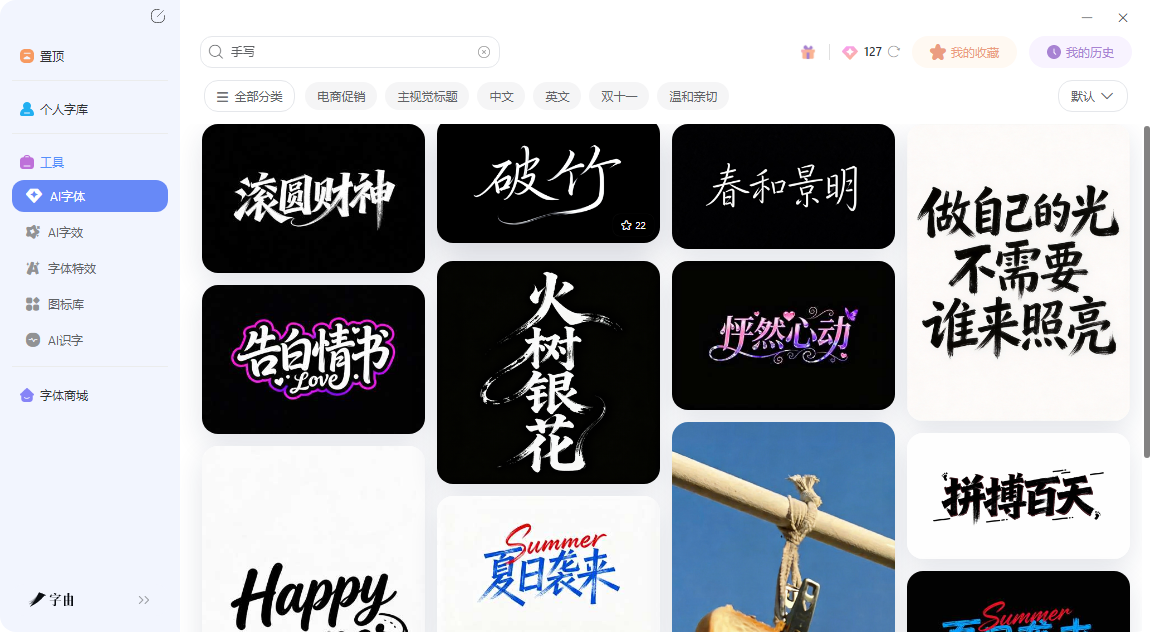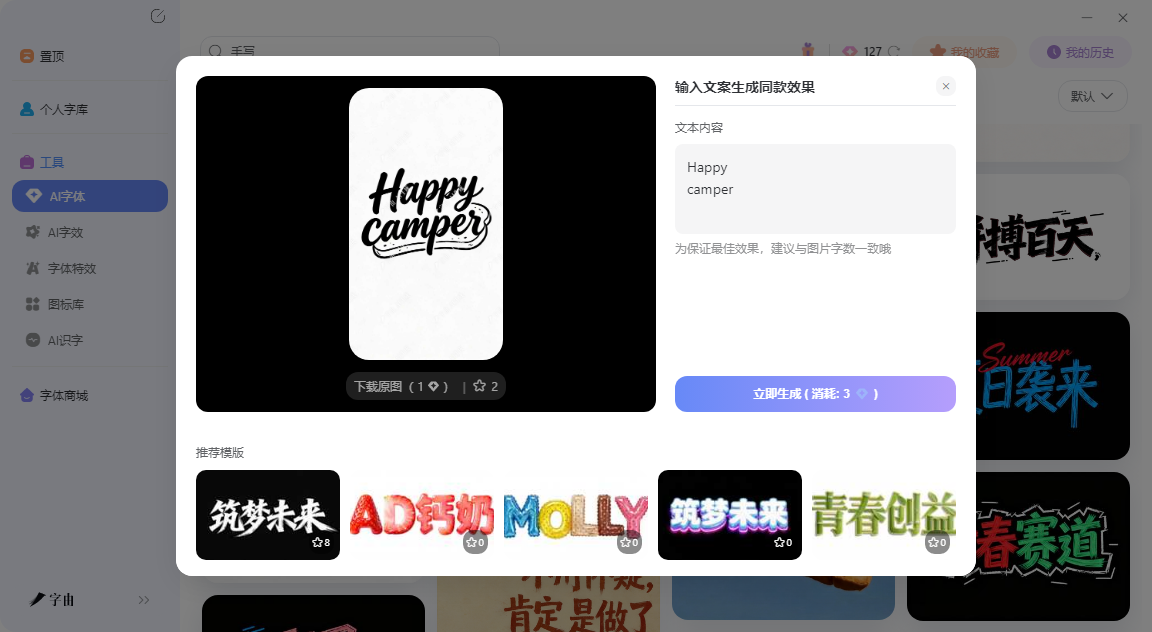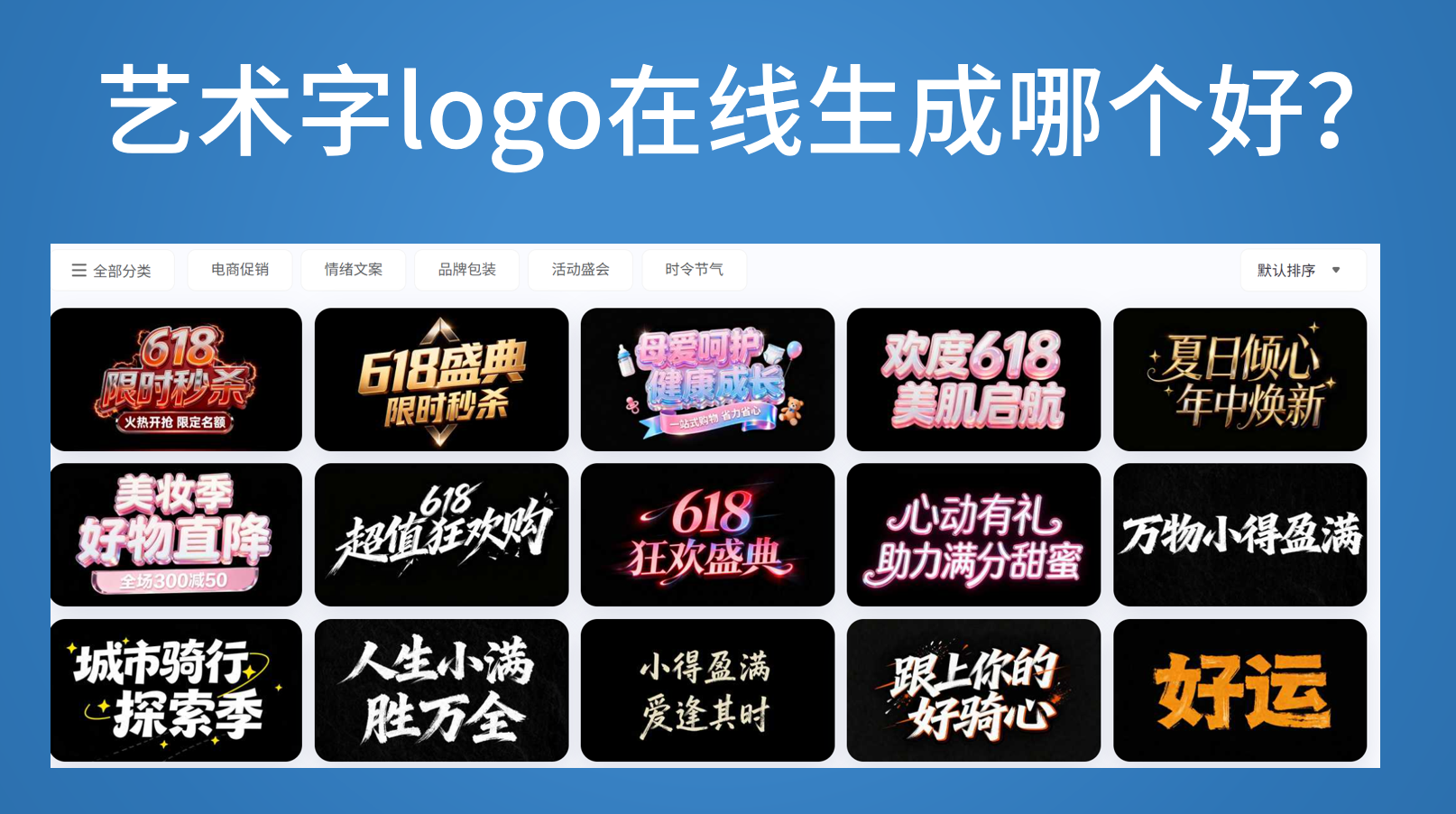
艺术字logo在线生成哪个好?零基础也能做出专业感
奶茶店“喜茶”、咖啡品牌“瑞幸”、科技公司“小米”——这些品牌的Logo,文字本身就是核心识别元素。如果你也想要这种效果,重点就在“艺术字”上:字体够不够有性格、排布够不够好看、能不能体现品牌调性。如果你需要的是图形+文字组合(比如一个动物图标加品牌名),那需要的是综合Logo设计工具,不光是字体的事。今天推荐的6个工具里,字由最擅长“文字型Logo”的艺术字生成,其他几个则是综合性的AI Logo设计平台,可以按需选择。
字由和其他Logo生成器最大的不同是:它不生成图形图标,只做一件事——把文字变得有设计感。打开字由的AI字体功能,里面有400多套艺术字模板,按风格分成国潮风、霓虹灯、金属质感、手写书法、电商促销等十几个大类。每一套模板都是专业设计师调好的字体+特效+排版的完整方案。你需要做的就三步:选一个跟你品牌气质接近的模板,把模板里的文字换成你的品牌名,点生成。10秒后,一张艺术字Logo图就出来了。
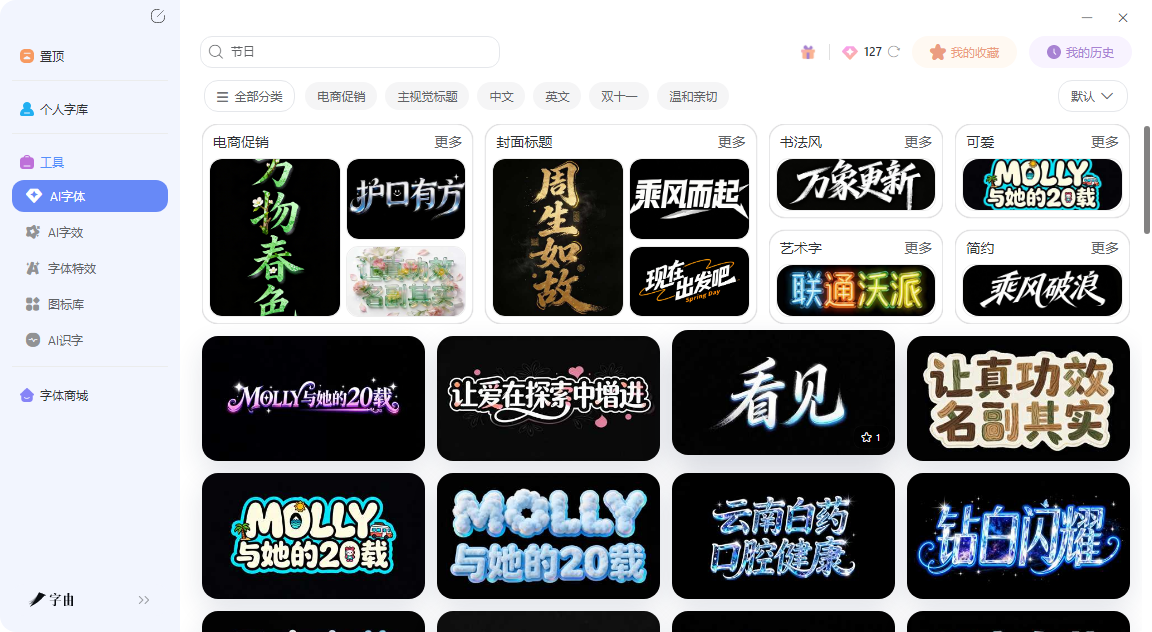
假设你开了一家手工皮具工作室,品牌名叫“一针一线”。打开字由AI字体,在“手写书法”分类里翻,找到一款笔触自然、带一点连笔的模板,把文字换成“一针一线”,生成。出来的效果像用毛笔写在牛皮纸上的感觉,跟品牌调性很搭。
为什么字由适合做文字Logo?因为文字Logo的核心就是“字体”。你不需要图形,不需要复杂排版,只需要那几个字够好看、够有性格。字由的400多套模板,本质上就是400多种“让字变好看”的现成方案。你不需要懂字体设计,不需要知道什么字体配什么效果,只需要选择模板就可以了。
如果你想要的是图形+文字组合的Logo,字由也够用,也因此字由是目前最快、最省事的方案。
2、AI Logo
第二个网站是一个AI Logo生成器。它的核心逻辑是:你输入公司名称和一段描述(比如“一家主打可持续发展的咖啡店”),AI根据描述生成多个Logo方案。操作分四步:描述愿景(输入公司名和关键词)→ AI生成概念(几十种方案)→ 定制完善(调颜色、字体、排版)→ 下载部署(获得矢量文件和网页格式)。这个流程适合那些“不知道自己想要什么风格,但知道自己是做什么的”用户。你不需要懂设计,只需要把你的业务说清楚,AI帮你出方案。
3、design
第三个是design。它自称“世界排名第一的AI Logo生成器”,它的Logo库有40万+模板,覆盖所有行业和风格。输入品牌名后,AI会生成数千个Logo方案供你选择。它还提供完整的品牌套件——Logo、名片、网站、社交媒体模板、邮件签名等,全部自动匹配你的品牌色和字体。它的优势在于规模。如果你想要海量选择,或者需要一站式搞定全套品牌物料,这个站很合适。付费方案提供矢量文件下载和商业授权,也有免费Logo可用(但功能受限)。
4、GoLogo
第四个是GoLogo。这是一个中文AI Logo生成器,首页显示已帮助374,898用户成功创建597,737个独特Logo。支持免费生成、可商用、矢量源文件下载。GoLogo的界面简洁,输入Logo名称即可生成。截图里展示了“Logogo”“Gologo”等多种文字Logo的预览效果,风格偏现代、简洁。它更懂中文品牌的需求,生成的Logo字体和排版对中文支持较好。如果你做的是国内品牌,GoLogo比纯英文工具更顺手。
5、SOLOGO
第五个是SOLOGO。它提供了三种AI Logo生成方式:名称转Logo(输入品牌名直接生成)、图片转Logo(上传图片让AI提取元素)、草图转Logo(手绘草图转成专业Logo)。还支持品牌套件生成、AI Logo样机、品牌图片生成等扩展功能。SOLOGO的“多模式”是亮点。如果你已经有灵感(比如一张参考图、一个随手画的草图),可以用图片或草图模式,让AI帮你完善。完全没想法就用名称模式。生成后支持矢量文件和动画格式下载,适合需要多用途输出的用户。
6、Deeplogo
第六个是Deeplogo。它的定位是“免费AI Logo生成器”,首页写着“30秒创建专业品牌标识”。输入公司名称,AI智能生成多种Logo设计方案,支持PNG/SVG高清下载,版权保护。Deeplogo适合初创企业、中小企业快速打造品牌形象。功能相对简化,没有复杂的定制选项,但胜在快、免费、够用。如果你只需要一个基础的文字Logo应急,Deeplogo是最轻量的选择。
做艺术字Logo,关键不是工具多高级,而是你能不能快速把想法变成看得见的东西。字由最适合做纯文字型Logo,400多套艺术字模板选一个改文字就行,生成的可商用,适合工作室、小店、自媒体;GoLogo适合需要完整品牌视觉系统的用户,从Logo到名片到网站一站式搞定;SOLOGO的多种生成模式适合有灵感但不知道怎么落地的用户;Deeplogo最简单最快,适合应急。打开这些工具,输入你的品牌名,生成第一个版本,不满意就换模板或者换工具。不要纠结“一次到位”,先有一个能用的,后面慢慢优化。零基础做Logo,现在就可以实现!